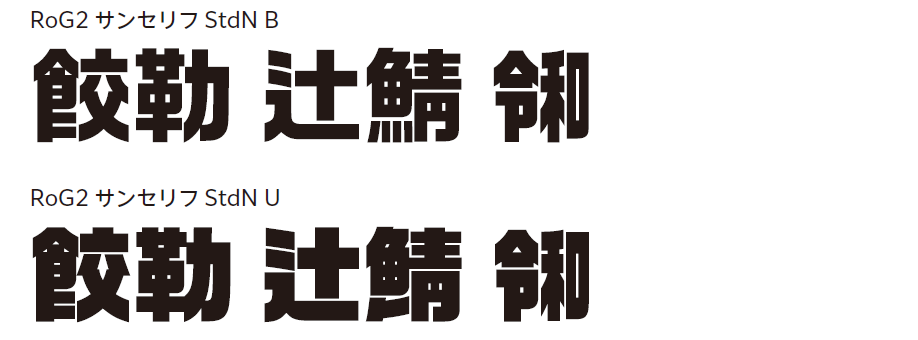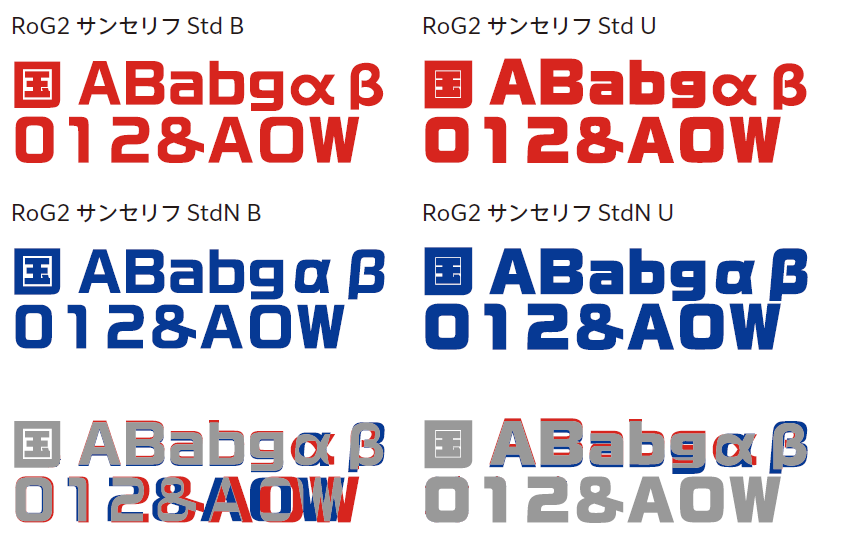
【StdN版のG2サンセリフについて】
StdN版のG2サンセリフは、Std版からグリフセットのStdNへの拡張(文字追加)、一部デザイン調整を行っています。
【StdN版で追加した文字について】
StdN版のG2サンセリフでは、従来のStd版に対して以下の文字を追加しています。
・Std(Adobe-Japan1-3)の文字数9,354文字に対する不足分の1,986文字
・文字セット[Std]に対して[StdN]で追加された144文字
・令和合字の1文字
追加文字の例
【漢字・略字のデザイン変更について】
StdN版のG2サンセリフでは、一部の文字を除き、Std版で採用されていた略字を見直し、略さないデザインに変更しています。
また、略字以外にも、デザインの見直しを行っています。
デザイン変更の例
【欧文、記号類のデザインについて】
StdN版のG2サンセリフでは、欧文、一部の記号類で以下の調整を加えています。
・ベースライン(文字位置)変更
・デザイン変更
・メトリクス情報変更
※注意
StdN版のG2サンセリフではメトリクス情報の変更が含まれるため、
Std版から書体を置き換えた場合は組体裁が変わります。
StdN版とStd版は互換性はありません。
デザイン、文字位置調整の例